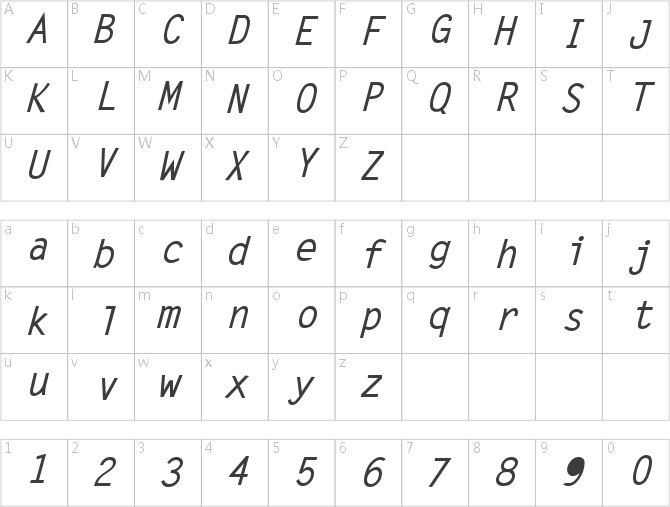
Letter-Gothic-Bold-Italic 詳情頁
Letter-Gothic-Bold-Italic字體字庫是一款讓人賞心悅目、百看不厭的英文字體,適合各類廣告和產(chǎn)品包裝設(shè)計應(yīng)用,字體大小0.05MB,格式為ttf字體,上傳用戶是迷路的豬,作者/版權(quán)方為未知